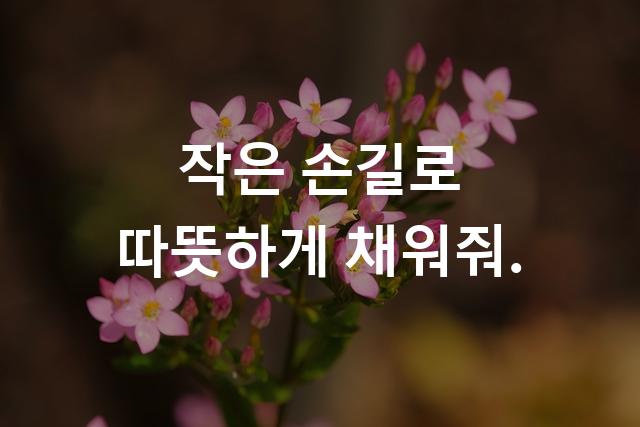
카카오 큰글씨는 카카오에서 제작한 기본 고딕 폰트로, 깔끔하고 읽기 쉬운 디자인이 특징입니다. 모던함과 심플함을 기반으로 한 디자인으로 다양한 매체에서 활용하기 좋습니다.
카카오 큰글씨은(는)
기본 고딕, 감성적인, 부드러움 계열의 생김새를 가지고 있으며
웹/앱 디자인, 보고서/문서, 일기/편지 등에서 자주 활용되며, 효과적인 메시지 전달에 적합합니다.
이 폰트는 기술/IT, 유아/가족, 금융/비즈니스 분야에 잘 어울리며,
명확한, 편안한, 단순한 느낌을 담고 있는 것이 특징입니다.